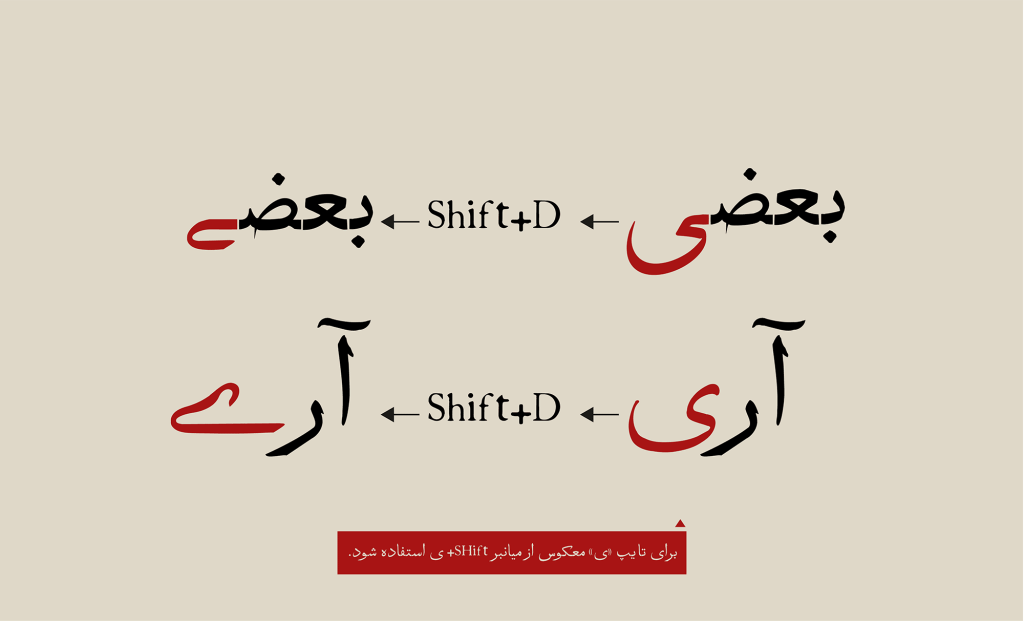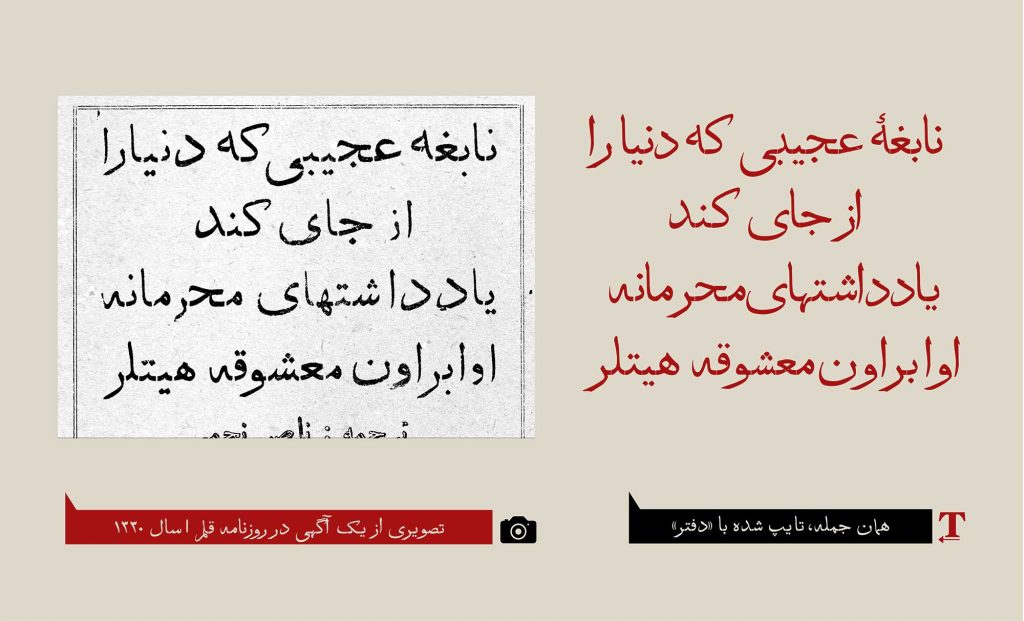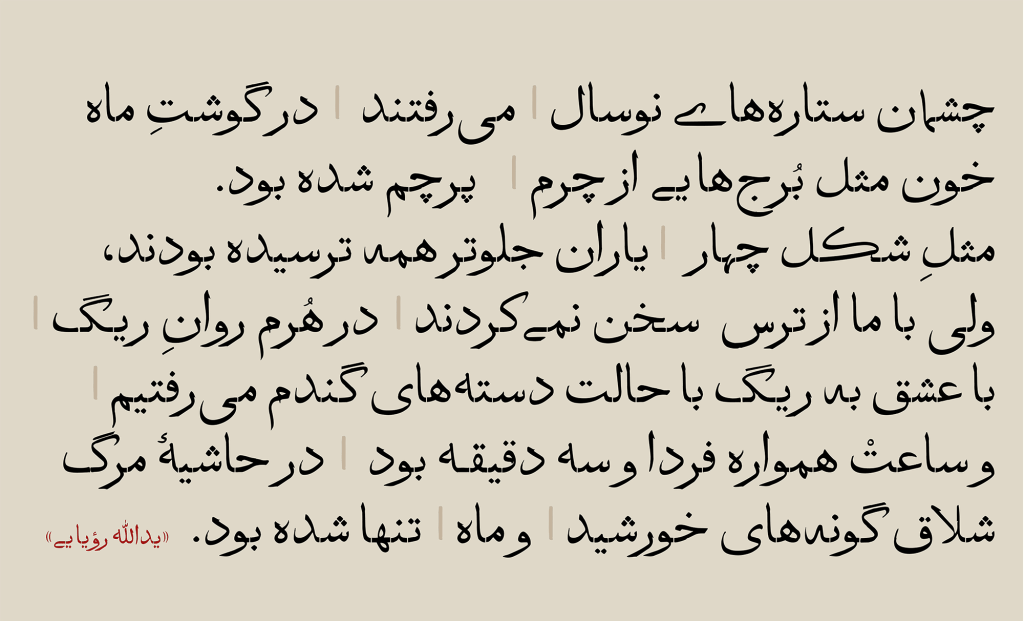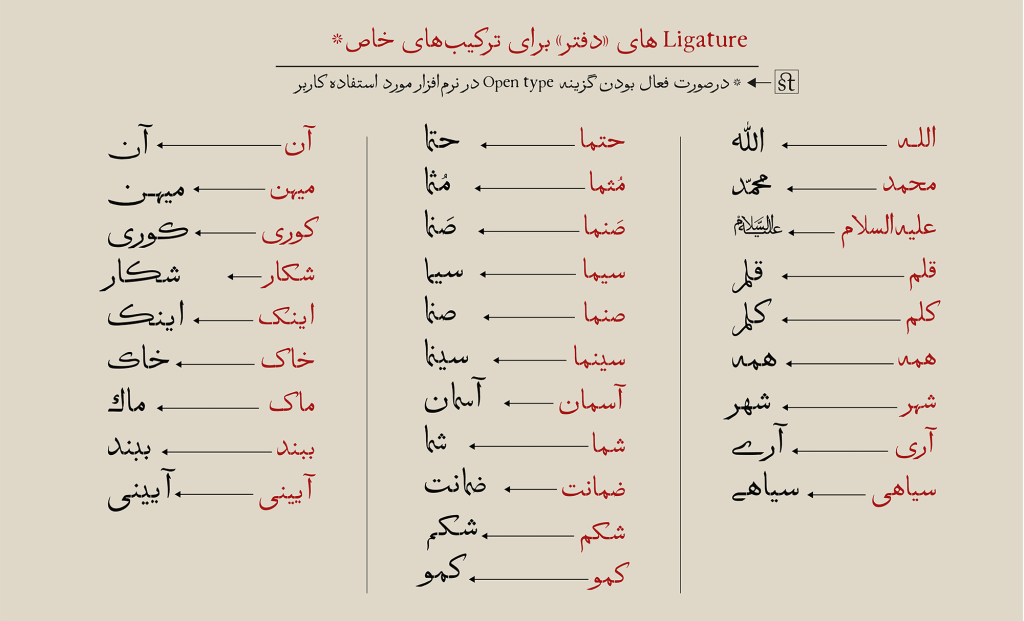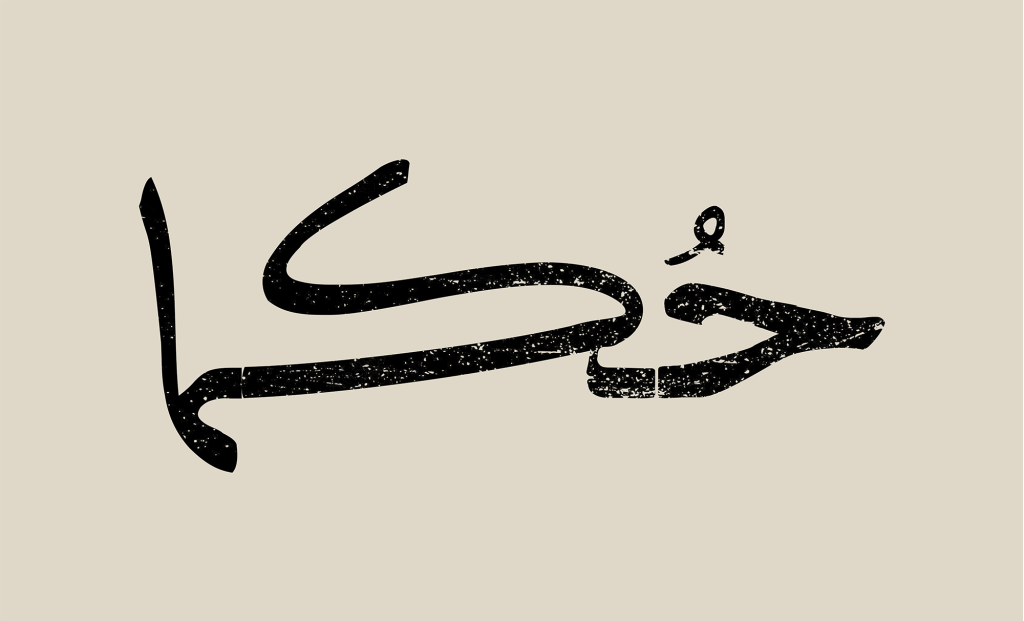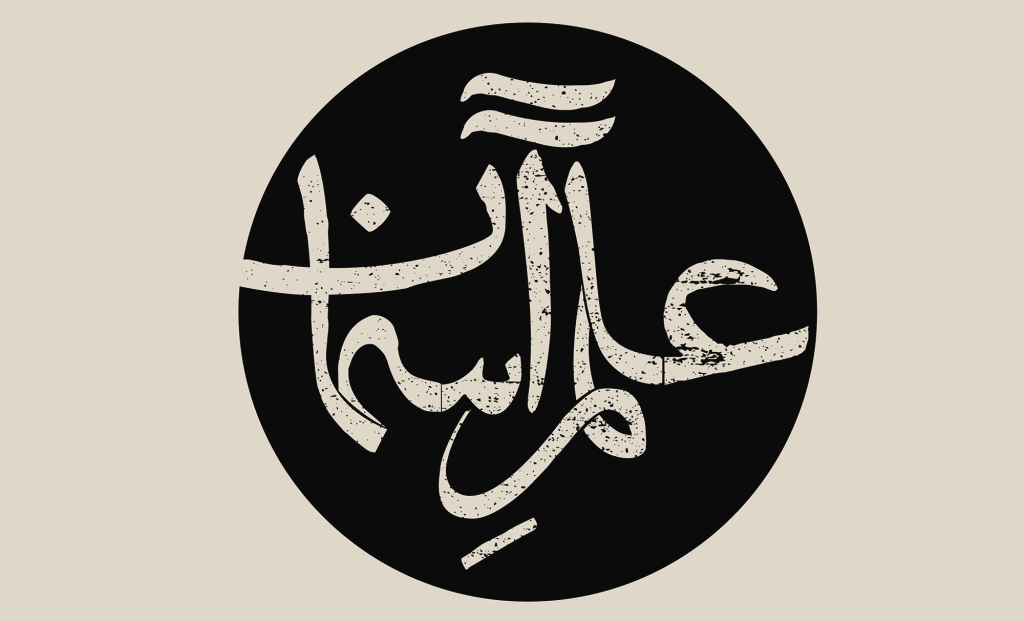
فونت دفتر
فونت دفتر برای خلق حس و حال کهنه و نوستالژیک ابداع و ایجاد گشته است،دفتر دارای کمی خوردگی، بی نظمی در اتصال حروف و عدم تناسبات به صورت عامدانه می باشد.
بنابراین گرچه این حروف در زمان خود ویژه اعلانهای رسمی بوده است اما اکنون یک فونت نمایشی محسوب میشود و بیشتر مناسب آثار گرافیکی با حال و هوای قدیمی (نوستالژیک) است.
طراحان گرافیک، طراحان فضای مجازی و وبسایت، ناشران، مطبوعات، طراحان صحنه، هنرمندان و همهی آنها که به نوعی با فونتهای فارسی سروکار دارند، همواره با کمبودِ حروفی با حال وهوای قدیمی، برای ساخت فضاهای نوستالژیک مواجه هستند.بههمین دلیل، هر وقت پای اِلقایِ حسّی قدیمی به کمک یک فونت به میان میآید، یا باید بیخیالش بشویم یا با دستکاریِ نمونههای موجود، عجالتاً کارمان را راه بیندازیم!
قدمت این فونت که امروز؛ با نام «دفتر» نامگذاری شده است؛ به روزنامهها، آگهیها و کتابهایی برمیگردد که حدود یک قرن پیش به شیوهی «چاپ سُربی» منتشر میشدند.